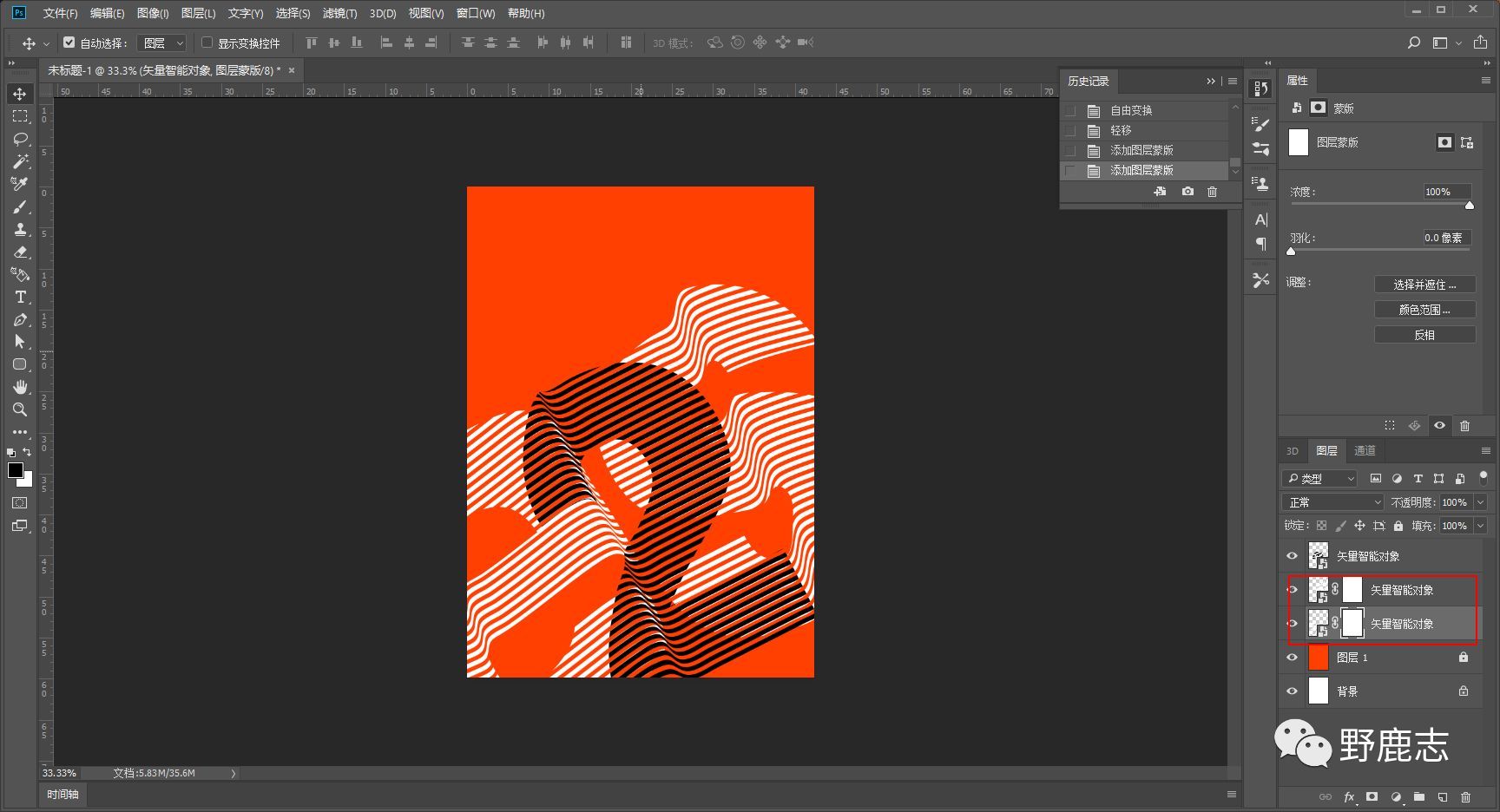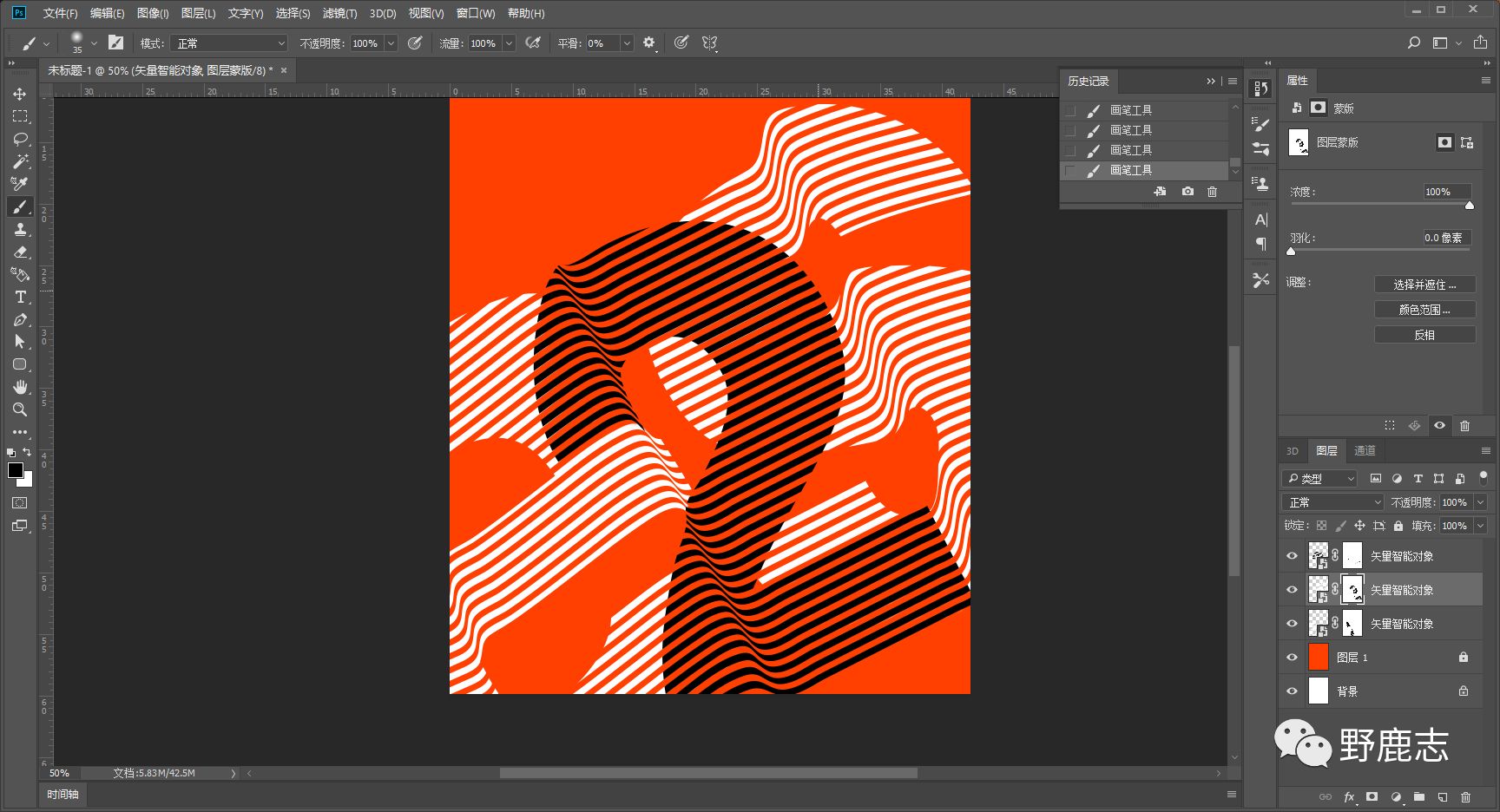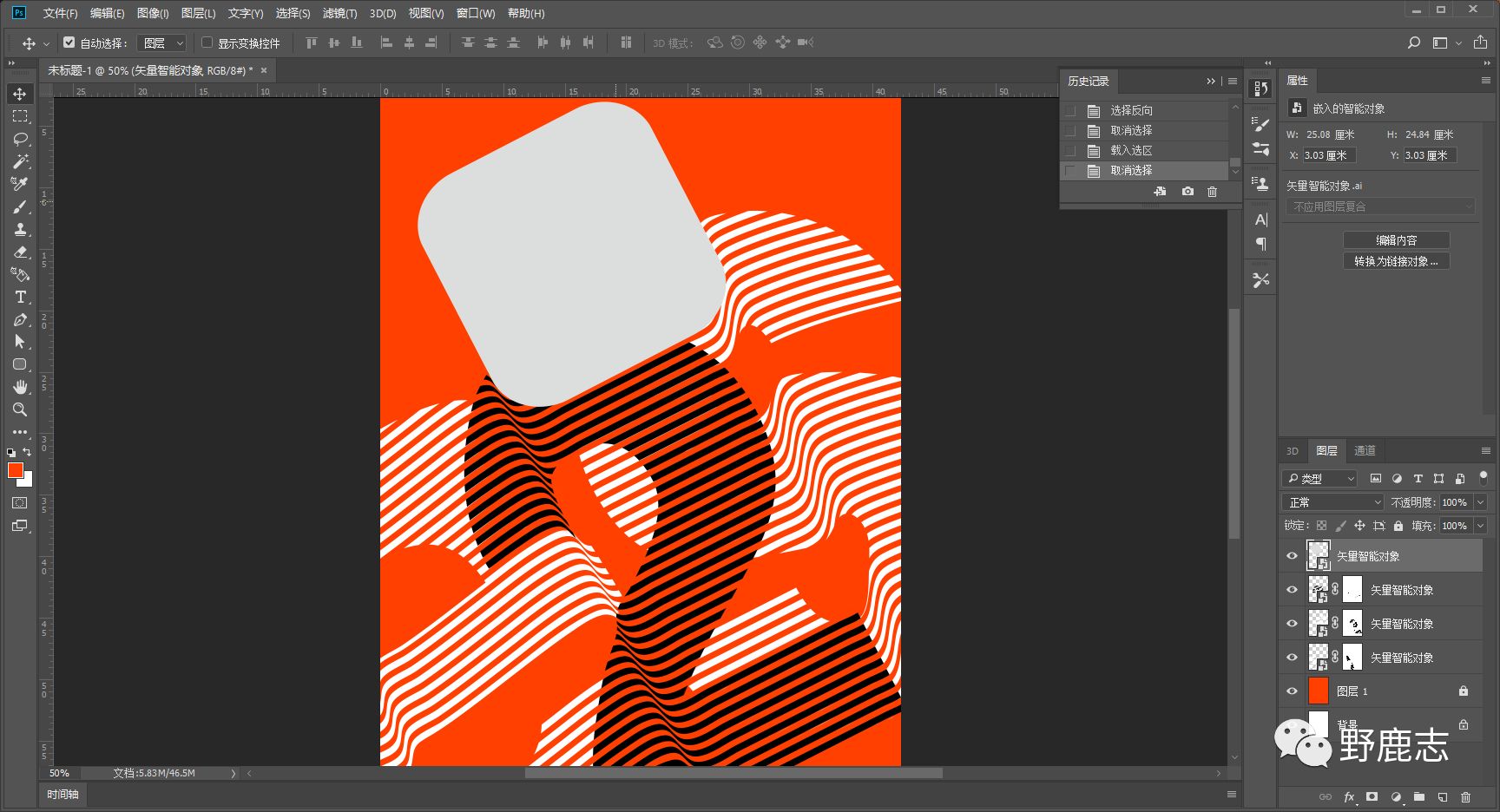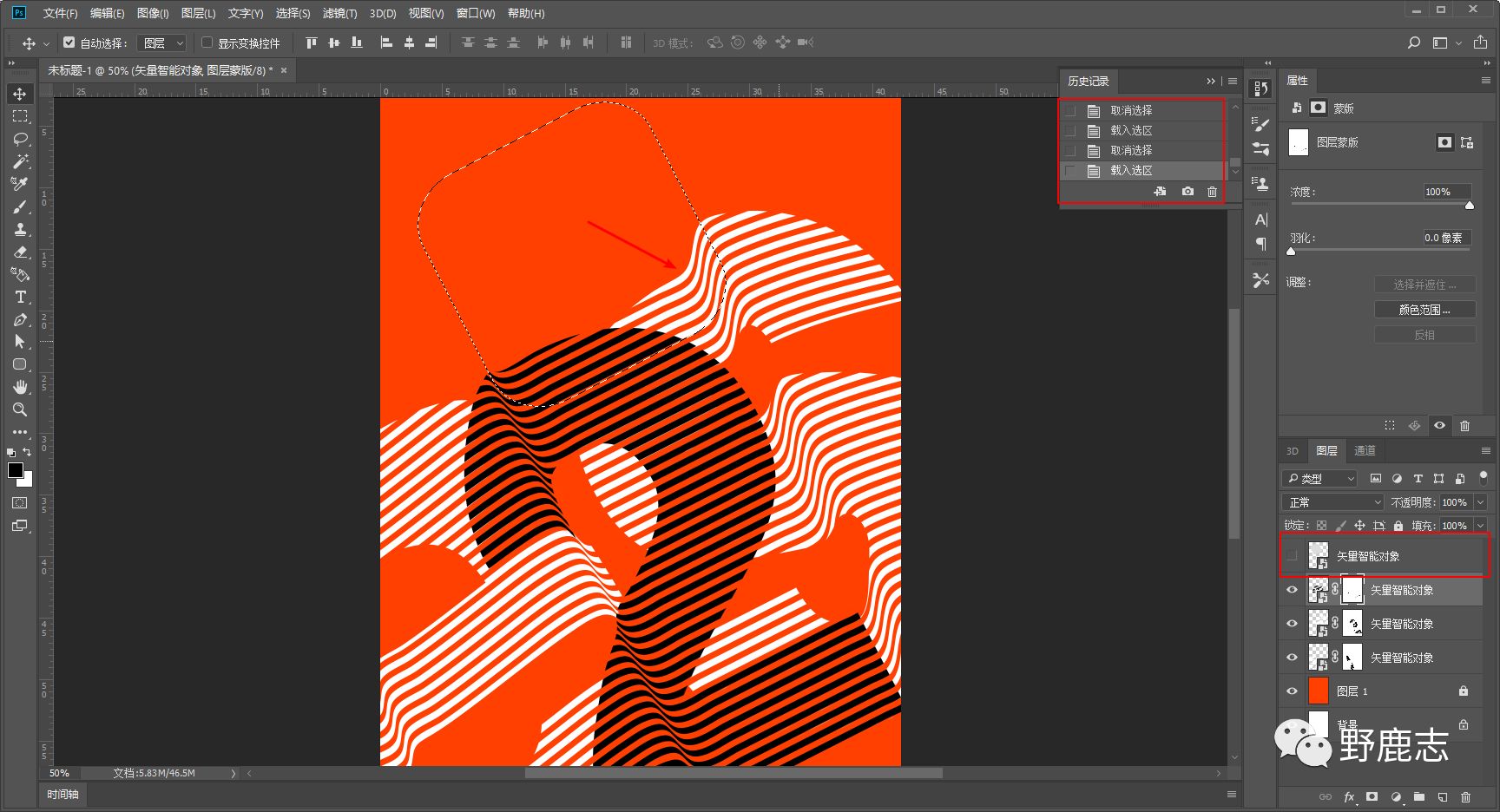
这种效果其实用Ai封套扭曲来制作并不是很难,和我野郎前面分享的丝带数字一样,主要是考究锚点以及手柄的调整:
来吧,今天我们就用Ai和Ps制作这幅简约的扭曲效果海报吧!
打开Ai,新建画板,尺寸随意:
为了方便观察,先给个背景色吧,在画板上画一个矩形,并且ctrl+2锁定:
矩形工具画一个长条,执行效果-扭曲和变换-变换:
把预览打上勾,副本上输入数值,然后再在垂直方向给点参数,这样长条矩形就被复制出来了。
具体参数大家可以不用和我一样,自己看着来比较好:
然后再执行对象-扩展外观:
路径查找器面板选择联集,将其合并为一个形状:
按住Alt键拖动复制出来两份,并将其中一份颜色改为黑色,放一边:
找一个合适的字体打上文字,我这里选择的是Swis721 Blk BT Black。
ctrl+shift+o轮廓话,调整好大小之后分别置于不同的线条对象的上方:
分别选中三组对象,执行ctrl+7创建剪切蒙板:
调整它们的位置关系,大概如图所示的样子:
执行对象-封套扭曲-从网格建立,行4列4:
因为我觉得从网格建立的等分线不太好调整,所以用网格工具另外加了两根线:
接下来就是用小白工具去调整锚点和手柄啦,我觉得这个就是多练习吧,没啥其他的技巧,调完以后大概这样:
选中再次执行对象-扩展:
再取消编组,多取消两次,将3个文字分离开来:
再画一个圆角矩形比对好大小吧:
其实至此要求不高的童鞋只有Ai就可以搞定了,只是有强迫症的野郎觉得箭头所指出多出来的部分碍眼,到Ps里搞比较方便:
所以先把文字的各个部分拖进Ps里,摆放好位置和大小,然后分别添加图层蒙板:
然后再用黑色画笔在图层蒙板上擦去让你觉得强迫症的地方:
把刚才画的那个圆角矩形也拖进来:
载入圆角矩形的选区,将圆角矩形隐藏掉:
再在对应的图层蒙板上擦去不需要的部分:
这样基本上就算完工了,最后再简单的码字、排版、导样机看看效果吧:
个人觉得还是有些相似。
其实很多类似视觉错的文字类海报都可以利用封套扭曲来制作,只要大家多多练习手柄以及锚点的调整就好。